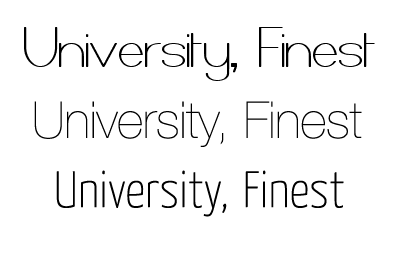
Edel, elegante Schrift?!
Ich suche eine Schrift für ein Logo, sie sollte edel, elegant aber trozdem modern wirken...
Da Meinungen ja bekanntlicherweise verschieden sind, würde ich gerne wissen wie ihr diese Schrift dazu findet.
Ich freue mich auch wenn ihr andere Vorschläge oder Tipps habt.
Edel, elegant und modern...
Ich würde mir mal holländische Schriften genauer ansehen, beginnend bei underware, da wahrscheinlich vor allem Dolly, und endend bei TEFF und DTL.
Besonders die letzten beiden Schrifthäuser sind wirklich sehr edel :wink:
Vielleicht tut es bei entsprechendem Einsatz auch eine Quadraat, Scala oder Fedra?
also Edel und Billig (gratis ist ja seeehr billig) ist ja eigentlich ein Widerspruch in sich.
Versuchs mal mit Charis SIL oder Gentium – wenn’s eine Serif sein darf.
Serifenlos fällt mir jetzt nichts ein. Aber ich bin schon mal auf weitere Antworten gespannt.
Eigentlich ein Widerspruch... aber na gut
Serif: Die Lido von stormtype.com gibt (gab?) es auch kostenlos.
Sans: die Yanone Kaffeesatz müsste es auch noch kostenlos geben
Ich denke das die Schrift schon Serifenlos sein sollte...bin mir nicht sicher aber alle die ich ausprobiert habe mit Serifen kommen irgendwie nicht so elegant rüber...
Warum darfs nicht mal eine Freeware schrift sein?!
Ist ja jetzt kein riesen Projekt, wo ich Geld für bekomme.
die ich schon rausgesucht hatte, sehr passend.
Allerdings brauch ich ja noch einige alternativen, weil eine ist zu wenig.
edel und elegant könnte auch eine Schreibschrift sein, diese würde dann allerdings wie ich finde, wiederrum eher nicht modern (für junge Leute) wirken und nicht zum Projekt passen.
Ich finde die Schrift weder ‹edel› noch ‹elegant›, sondern – schlicht ein Graus. Hast Du Dir die «Kaffeesatz» schon angesehen?
ja habe ich...die ist auch ganz ok, aber das sie elegant oder edel wirken soll kann ich da nicht wirklich drin erkennen...etwas schon, aber jetzt nicht auf den ersten Blick.
Ich habe aber auch schon andere Leute gefragt wie die castorgate schrift bei ihnen rüberkommt wenn sie die sehen...alle meinten elegant und auf jeden fall was was zusammenpast...fein, edel etc...
vielleicht ist es auch ein wenig Geschmackssache.
Selbstverständlich ist es Geschmackssache, welche Schrift einem gefällt. Das ist auch nicht das Problem. «Kaffeesatz» ist eine von einem Profi sorgfältig durchgearbeitete Schrift, während «Castorgate» sofort als dilettantischer Gratisfont erkennbar ist. Vor allem die angebotenen Varianten sind eine Zumutung für das Auge – als hätte jemand zum ersten Mal mit einem Graphikprogramm herumgespielt.
also die Kaffesatz ist schon gut...allerdings sollte es noch eleganter aussehen.
Ich finde so Schriften die sehr dünn sind und ohne Serifen kommen meistens sehr elegant rüber (deswegen war mir die Castorgate ebend zuerst aufgefallen), die anderen Varianten der Schrift interessieren mich gar nicht ;)
Da ich aber kein Profi bin, würde ich jetzt nicht auf den ersten Blick sehen das diese Schrift, naja sagen wir mal so "schlecht gemacht" ist...
woran erkennt man das bitte :lol: ...ich hab leider keine ahnung*g*
"Deine" Schrift ist ein gar gräuslicher Graus, echt... lass es!
>Ich finde so Schriften die sehr dünn sind und ohne Serifen kommen meistens sehr elegant rüber
Falls dem so sei...
Die Helvetica Neue 25 Ultra Light hast du nicht zufällig in deinem Schriftenköfferchen?
Ansonsten - nur einen Schriftschnitt zu kaufen, ist ja wohl auch nicht die Welt.
ja stimmt die Helvetica ist auch gut...werde ich mal probieren...
ich bin aber laie...kann mir hier irgendjmd sagen warum die castor schrift ein graus ist? sorry versteh das gar nicht :lol::lol:
Ein Bild sagt mehr als tausend Worte, oder?
Man sieht doch gleich wie unmäßig die Buchstabenformen deiner Schrift angelegt sind, die Abstände der Buchstaben zueinander sind auch völlig daneben...
1. Deine Schrift
2. Helvetica Neue 25 Ultra Thin
3. Kaffeesatz Thin
Auf den ersten Blick und sicher unvollständig:
- die Kurven sind schlaff (siehe bei U e n)
- teilweise Kopflastigkeit (siehe s B k)
- die Form des t ohne Schweif unten ist falsch (ok, das könnte man der Futura ach vorwerfen)
- allgemeine Scheußlichkeiten: G Q 2 4
- Die Buchstabenabstände sind viel zu eng bzw. unausgewogen. Wahrscheinlich fehlendes Kerning
okay die Buchstabenabstände finde ich auch sehr daneben, aber die hätt ich dann einfach per hand verändert...
Die Helvetica gefällt mir allerdings auch sehr gut im Beispiel...sieht für jedermann auf den ersten Blick auch ähnlich aus.
vor kurzem (oder immer noch) waren z.b. slabserif-schriften in der «hippen jugendkultur» ziemlich… äh… hip, wenn ich das richtig mitbekommen habe.
(und ja, ich sage bewusst slabserif. der erfinder der din-norm - inkl. der so poetischen bezeichnung serifenbetonte linear-antiqua - sollte für alle zeiten ausser landes verstossen und an einen voller setzenkasten gebunden in eine grube geworfen werden)